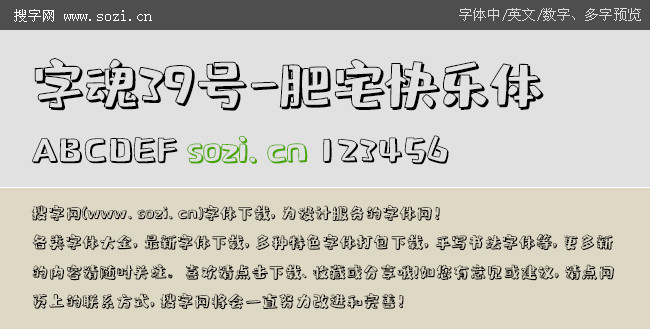
字魂39號(hào)-肥宅快樂(lè)體
搜字網(wǎng)提供一款字魂39號(hào)-肥宅快樂(lè)體中文字體下載,該字體是一款創(chuàng)意字體,該字體包含6763個(gè)中文、字母、 符號(hào)和數(shù)字,具有卡通、創(chuàng)意、有趣 的風(fēng)格,可以滿足您設(shè)計(jì)上的各種需求,該字體主要用于企業(yè)店鋪、廣告、影視傳媒、新媒體、電商、媒體、活動(dòng) 等場(chǎng)景。
- 風(fēng)格類(lèi)別: 海報(bào)POP體